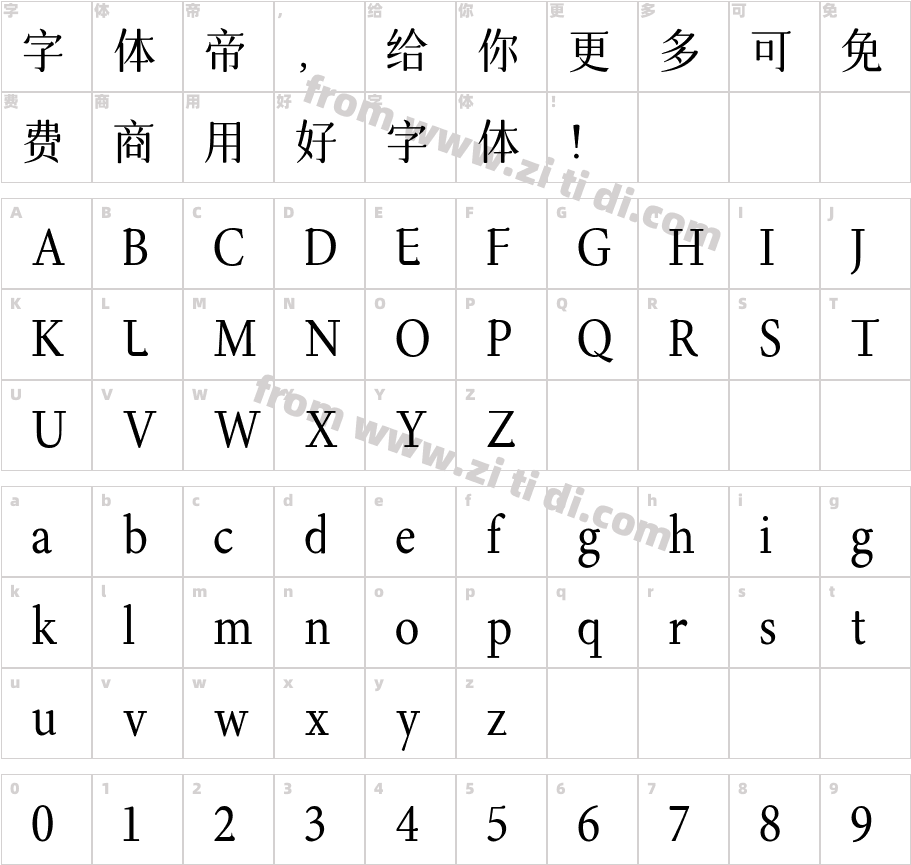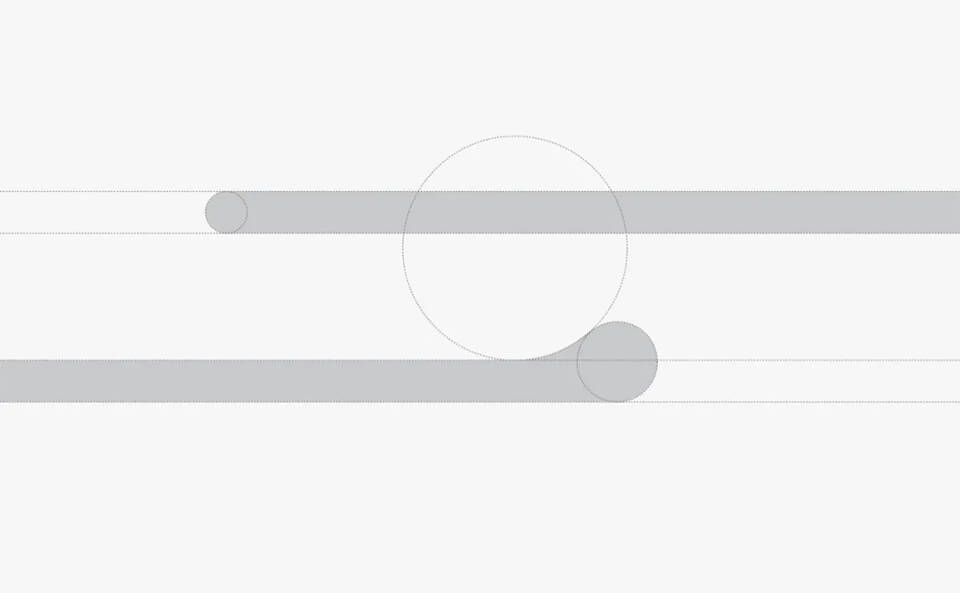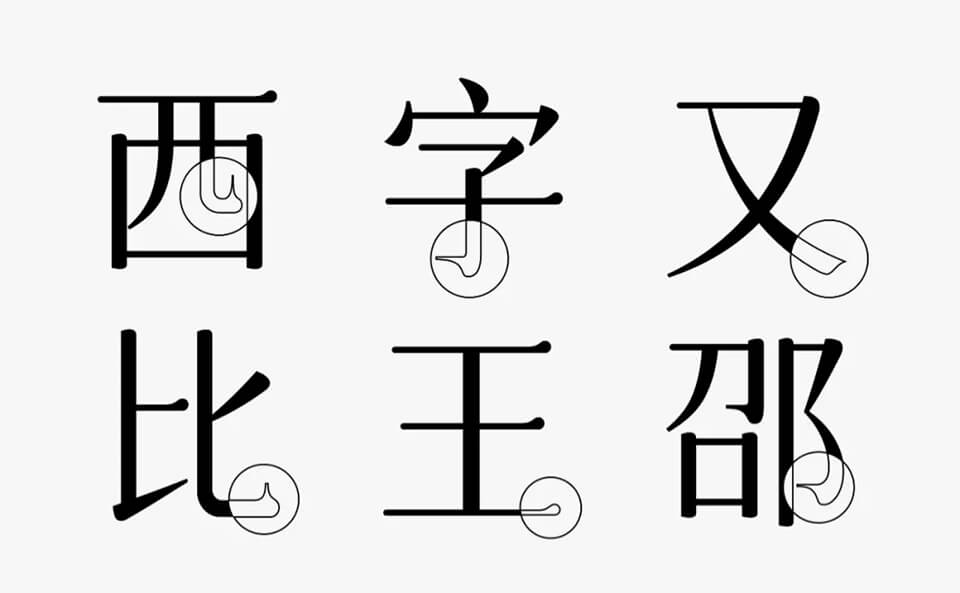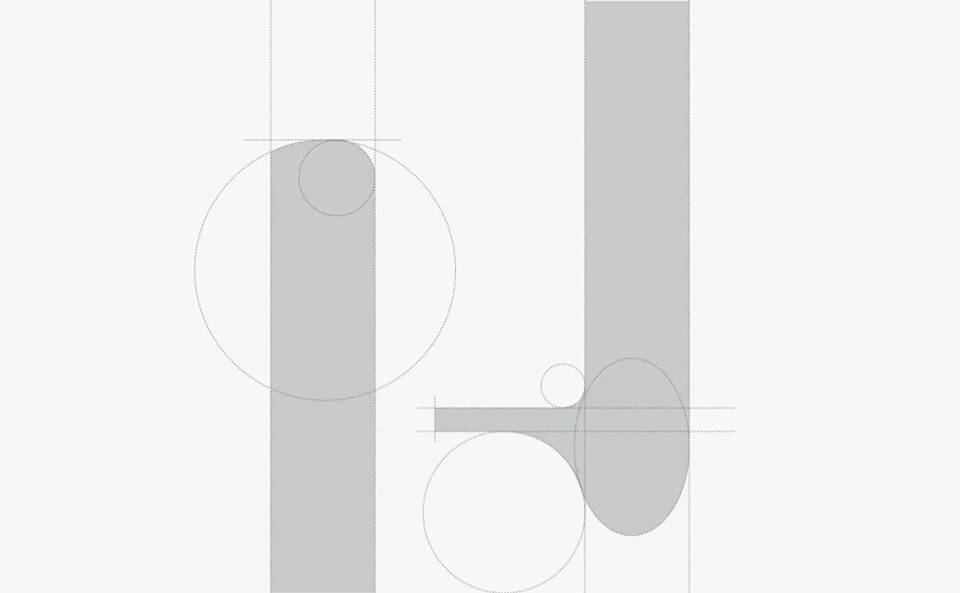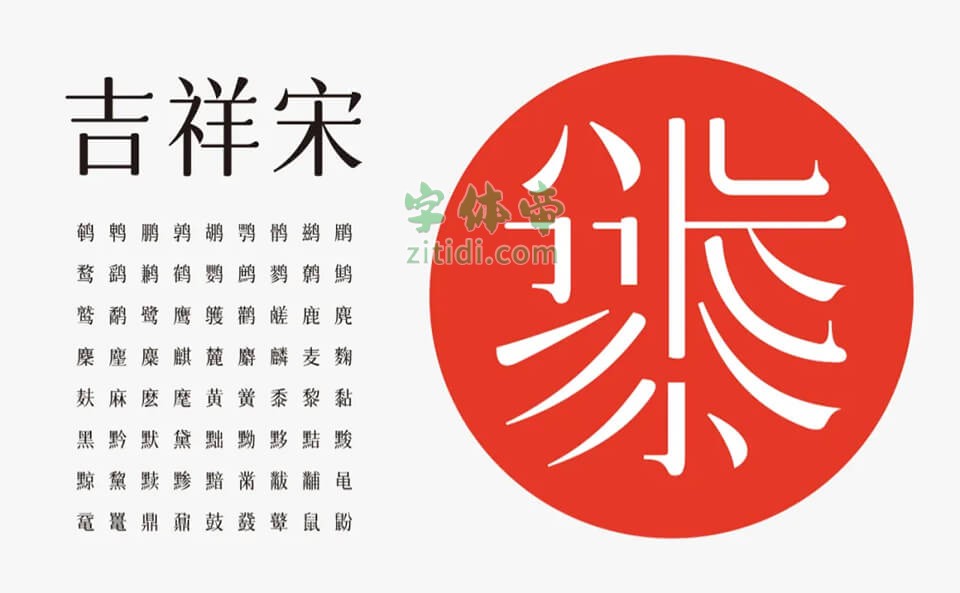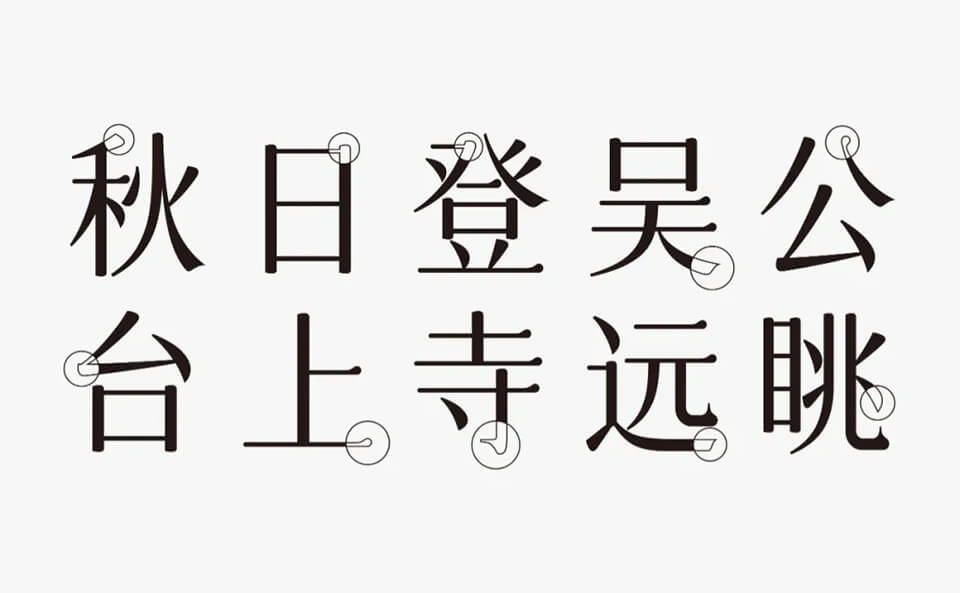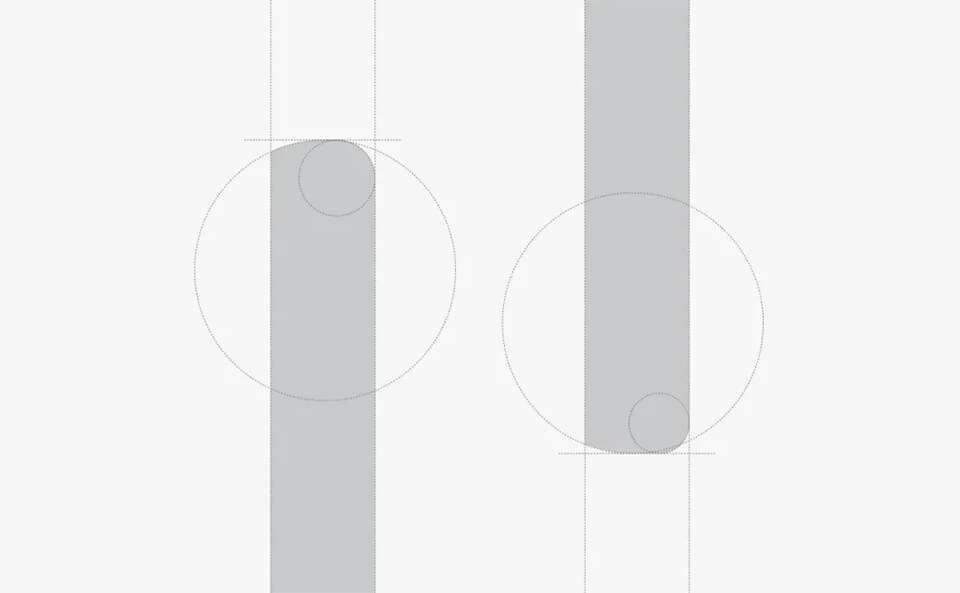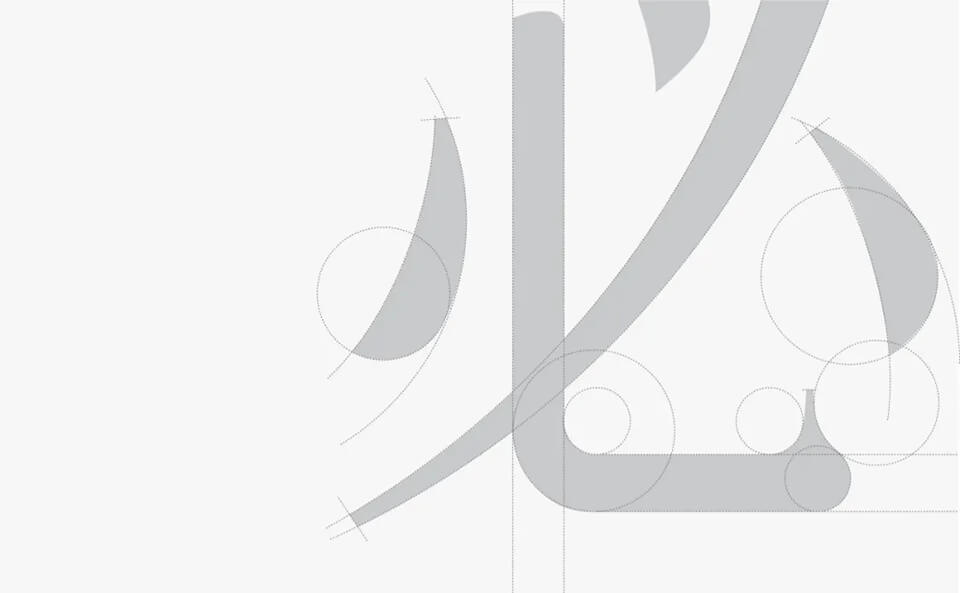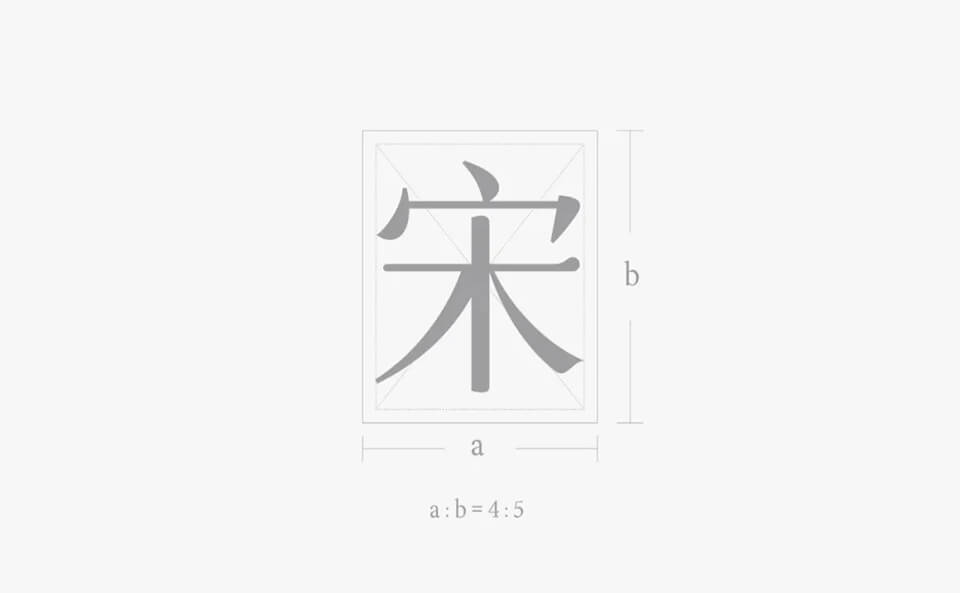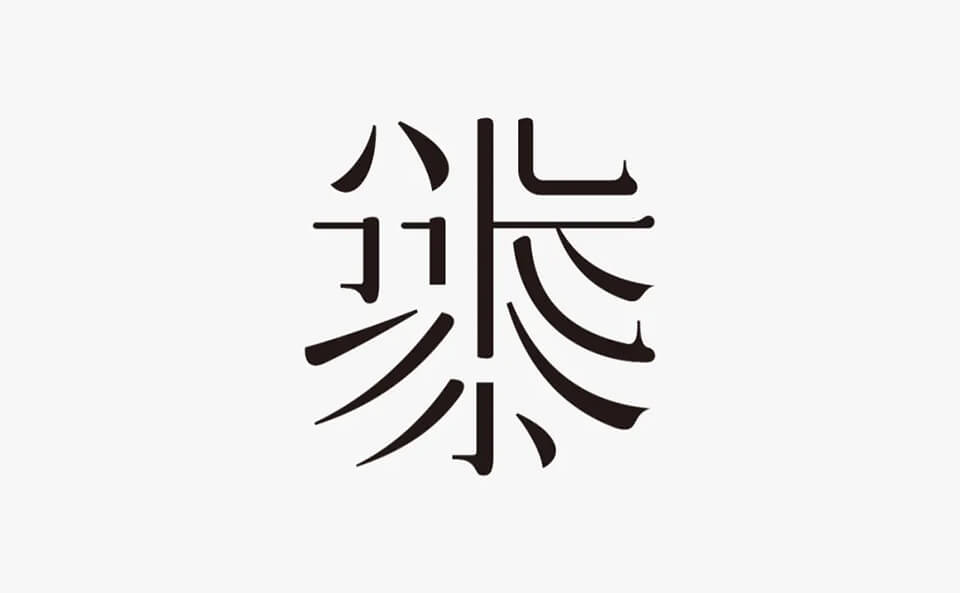
字体圈欣意吉祥宋涵盖国家GB2312编码标准的6763个中文字符,52个英文字符,10个阿拉伯数字,若干个标点符号,按需添加若干生僻字,共7000余字符。这是一套宋体风格的标题字,风格整体偏圆润古风,目前市场上免费商用的宋体字,除了思源宋体,好像就是思源宋体的修改版,没有专门设计风格的宋体字。
字体命名原本打算跟风格相同,欲名为“润宋体”,但没有什么特殊意义,毕竟免费字体可遇不可求,2020年确实是困难的一年,从年头到年尾非常艰难的度过,后来决定今天发布后,想到两个词“吉祥”与“平安”,纠结了好一会,最终定为“吉祥宋”,全名:字体圈欣意吉祥宋,很优雅的一个名字,我很喜欢,祝您今后每一年都能吉祥如意平安顺遂!
这款字风格圆润,比如横画开头及结尾设计较圆润的风格,竖画也变成圆润无尖凸风格,竖勾撇捺点的笔画同理。
整套字形视觉感偏瘦高,宽高比例为4:5,因为像这种圆润纤细古风女性化的字体,都是比较修长才好看。
“字体圈欣意吉祥宋”是一款书写很新颖的字体,字体大方,适合各种设计作品使用!欢迎下载!